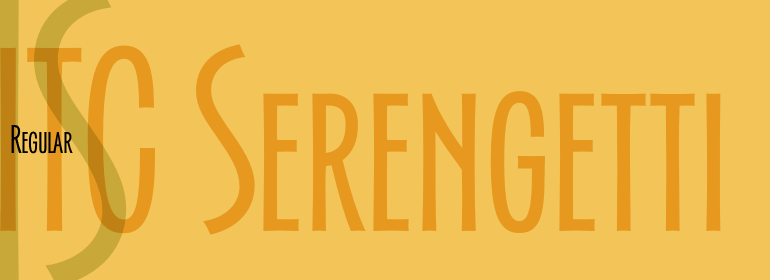
ITC Serengetti™
ITC Serengetti™,这款字体结构工整、笔画清晰,兼顾美观与易读性,适用于标题、正文、海报、包装、LOGO 等多种场景。字形优雅稳定,风格百搭耐看,适配日常排版与创意设计,让文字呈现更舒适、更具质感。ITC Serengetti™一笔一画,皆是细节,以均衡的比例、流畅的线条打造舒适视觉体验,字形端正大气,风格简约现代。无论是商业设计、品牌宣传还是日常排版,都能轻松驾驭,让文字更有格调与力量。ITC Serengetti™字体下载。
字体品牌: ITC(Monotype) 设计师:Alonso,Bob 字体分类:无衬线体 字体属性:外文 字符集:Unicode 发布时间: 2018